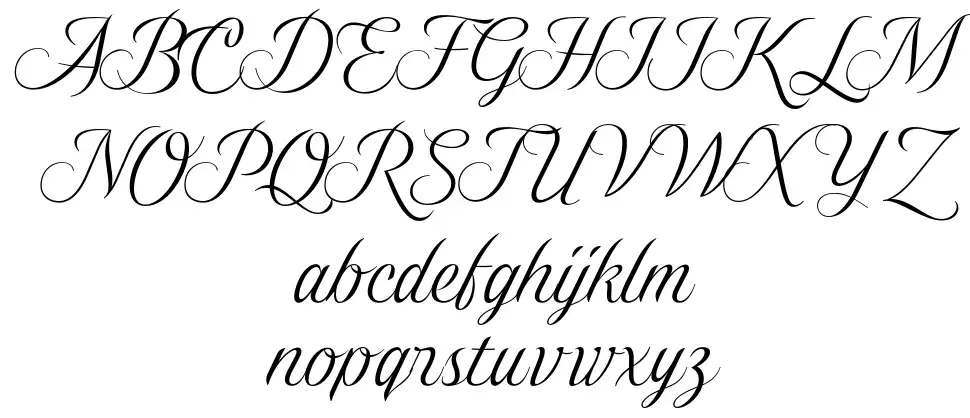
Gold Lines Schriftart _ Gold Fonts
Gold Lines has been downloaded 1,148 times.Gold Lines, crafted by renowned designer Eko Bimantara, is an exquisite calligraphy font.
Gold Lines à € von Eko Bimantara. Auch im Grafikdesign wird es gerne eingesetzt, wenn ein Design oder ein Element ganz besonders edel wirken soll.
Gold Lines Schriftart
Gold Lines Font